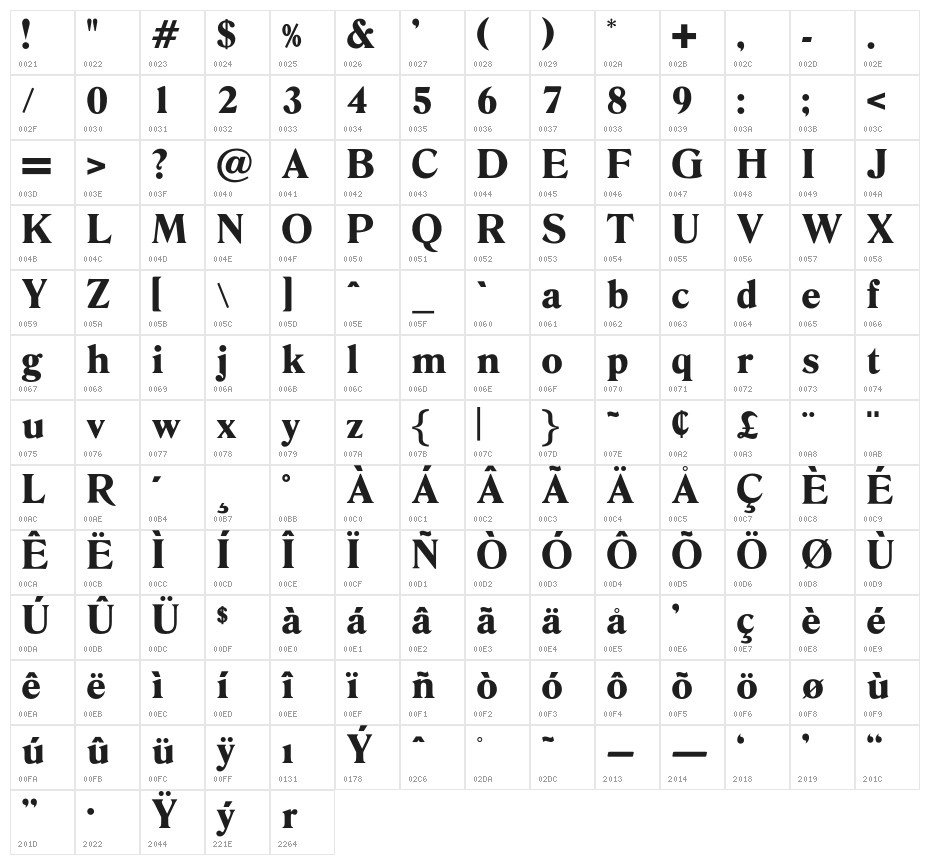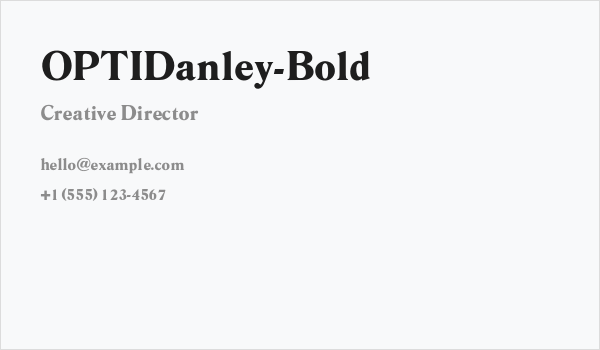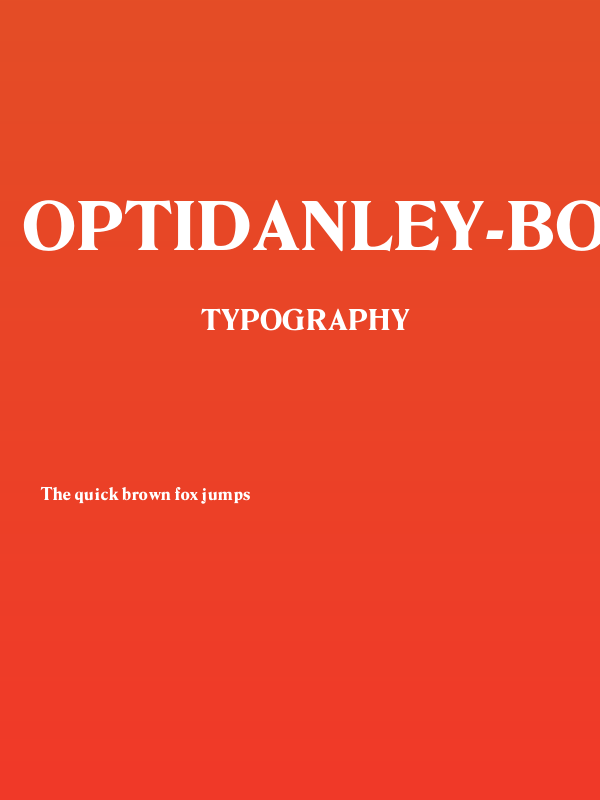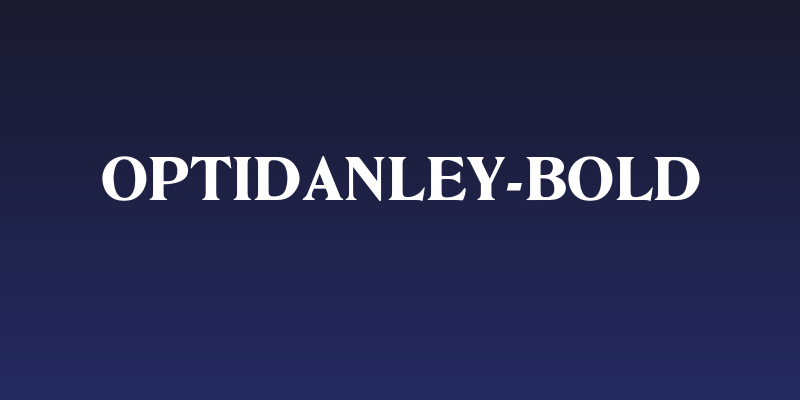
OPTIDanley-Bold Font
| Caso d'uso | Headlines, Logos, Branding |
| Progetti proposti | Ideal for branding, advertising, book covers, and any project requiring a strong, authoritative typeface. |